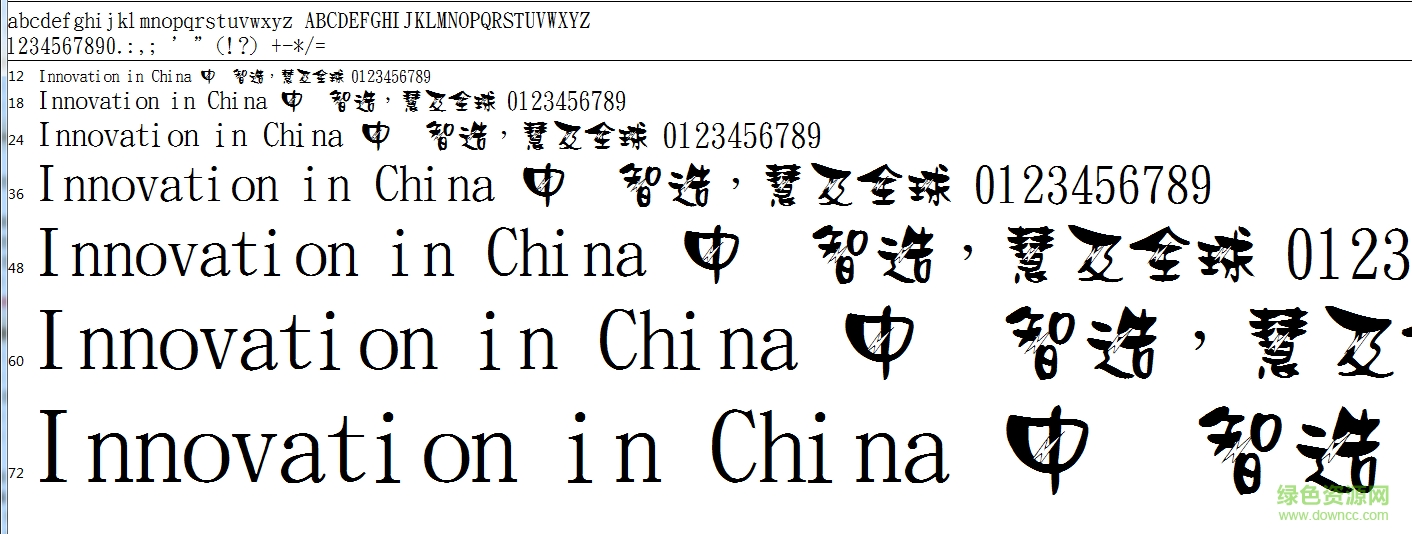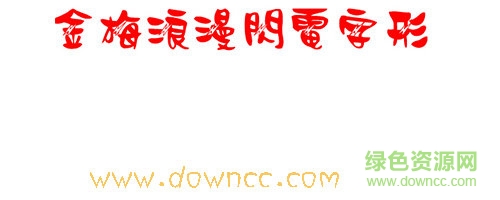
金梅浪漫閃電字形字體是一款將浪漫元素與閃電圖案相結(jié)合打造的創(chuàng)意性字體。該字體廣泛應(yīng)用于產(chǎn)品包裝、電視臺(tái)廣告、電影、電視劇片頭以及內(nèi)容用字等領(lǐng)域,喜歡的用戶們可以來(lái)綠色資源網(wǎng)下載哦!
效果非常統(tǒng)一,且字庫(kù)完整,可以廣泛應(yīng)用于產(chǎn)品包裝、電視臺(tái)廣告、電影、電視劇片頭以及內(nèi)容用字等領(lǐng)域,有需要的朋友可以免費(fèi)下載收藏。